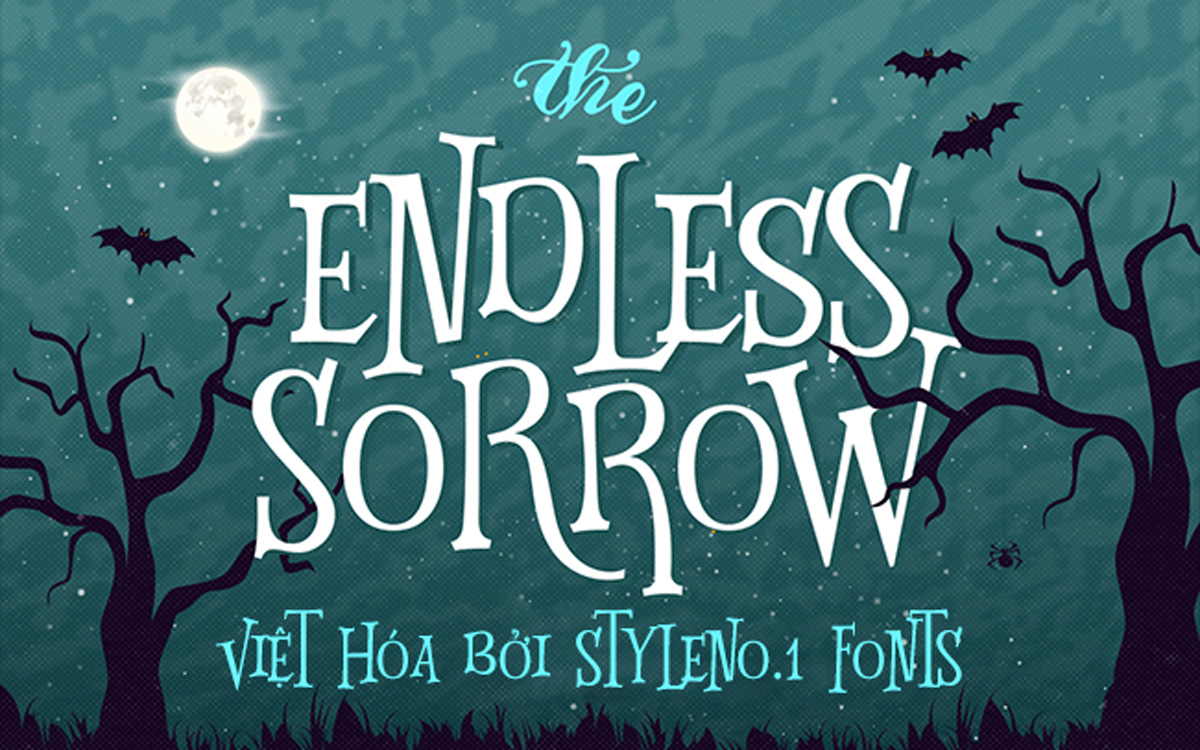
SVN-Endless Sorrow là font chữ mang phong cách hoạt hình pha trộn yếu tố kinh dị, nguy hiểm và bí ẩn, phù hợp với những thiết kế cần tạo ấn tượng mạnh ngay từ cái nhìn đầu tiên. Với đường nét độc đáo, giàu biểu cảm và không khí u tối đặc trưng, font chữ này có thể giúp tiêu đề, poster hoặc hình ảnh truyền thông trở nên nổi bật, khác biệt và dễ ghi nhớ hơn.
Không chỉ dành cho các dự án về Halloween hay phim kinh dị, SVN-Endless Sorrow còn có thể được ứng dụng trong thiết kế trò chơi, truyện tranh, sản phẩm giải trí, nội dung mạng xã hội và nhiều ấn phẩm sáng tạo khác. Nếu bạn đang tìm kiếm một kiểu chữ vừa có nét hoạt hình, vừa gợi cảm giác rùng rợn và nguy hiểm, đây là lựa chọn đáng để cân nhắc.
Font chữ hoạt hình, kinh dị nguy hiểm SVN-Endless Sorrow dành cho thiết kế sáng tạo ấn tượng
Font chữ hoạt hình, kinh dị nguy hiểm SVN-Endless Sorrow sở hữu diện mạo mạnh mẽ, khác biệt so với những kiểu chữ phổ thông thường thấy. Thiết kế của font hướng đến khả năng truyền tải cảm xúc trực tiếp thông qua hình dáng ký tự, giúp người xem nhanh chóng liên tưởng đến thế giới giả tưởng, những câu chuyện bí ẩn, không gian ma quái hoặc các tình huống đầy kịch tính.
Sự kết hợp giữa nét chữ vui nhộn theo phong cách hoạt hình và cảm giác bất an của chủ đề kinh dị tạo nên cá tính riêng cho SVN-Endless Sorrow. Nhờ đó, font có thể đóng vai trò như một yếu tố đồ họa quan trọng thay vì chỉ đơn thuần dùng để trình bày nội dung. Khi được phối hợp đúng với màu sắc, hình nền và bố cục, từng dòng chữ có thể trở thành điểm nhấn thị giác nổi bật trong toàn bộ thiết kế.
Phong cách hoạt hình kinh dị giàu cá tính
Điểm thu hút đầu tiên của SVN-Endless Sorrow nằm ở phong cách tạo hình mang tính biểu cảm cao. Các ký tự gợi cảm giác như được lấy ra từ một bộ phim hoạt hình kinh dị, một cuốn truyện tranh kỳ bí hoặc thế giới trò chơi chứa đầy thử thách. Tinh thần nguy hiểm, bất thường và có phần tinh nghịch giúp font tạo được dấu ấn riêng mà không cần sử dụng quá nhiều hiệu ứng trang trí phức tạp.
Đặc trưng này đặc biệt hữu ích khi thiết kế tiêu đề lớn, tên dự án, logo chữ, tên nhân vật hoặc những câu khẩu hiệu ngắn. Font có thể thu hút ánh nhìn nhanh chóng, đồng thời giúp người xem nhận biết chủ đề của sản phẩm ngay từ phần chữ. Để đạt hiệu quả tốt, bạn nên ưu tiên sử dụng SVN-Endless Sorrow cho các nội dung cần nhấn mạnh, thay vì dùng cho những đoạn văn dài đòi hỏi khả năng đọc liên tục.
Tạo tiêu đề nổi bật cho poster và ấn phẩm truyền thông
SVN-Endless Sorrow phù hợp để xây dựng tiêu đề có kích thước lớn trên poster phim, banner quảng cáo, bìa truyện, ảnh thumbnail, tờ rơi hoặc các ấn phẩm truyền thông theo chủ đề. Hình dáng chữ giàu cảm xúc giúp tiêu đề trở thành tâm điểm của bố cục, nhất là khi đặt trên nền tối, nền có chất liệu cũ, cảnh đêm hoặc hình ảnh mang không khí siêu nhiên.
Người thiết kế có thể khai thác font trong nhiều chủ đề khác nhau, chẳng hạn như:
- Poster Halloween, lễ hội hóa trang và chương trình giải trí theo chủ đề kinh dị.
- Bìa truyện tranh, tiểu thuyết giả tưởng, truyện ma hoặc nội dung trinh thám bí ẩn.
- Banner giới thiệu trò chơi, sự kiện nhập vai và các chiến dịch truyền thông sáng tạo.
- Thumbnail video kể chuyện, khám phá địa điểm kỳ bí hoặc phân tích phim kinh dị.
- Logo chữ cho thương hiệu giải trí, cửa hàng phụ kiện, sản phẩm nghệ thuật hoặc dự án cá nhân.
Khi ứng dụng font vào poster, bạn có thể tăng độ tương phản bằng cách sử dụng những màu sắc như đỏ sẫm, cam cháy, vàng cũ, trắng ngà hoặc xanh độc trên nền đen. Tuy nhiên, nên tiết chế số lượng hiệu ứng để giữ được hình dáng nguyên bản và khả năng nhận diện của từng ký tự.
Linh hoạt trong thiết kế nội dung số và mạng xã hội
Bên cạnh các ấn phẩm in, font chữ hoạt hình kinh dị SVN-Endless Sorrow còn có thể hỗ trợ sáng tạo nội dung trên môi trường số. Font phù hợp với ảnh bài đăng, ảnh bìa, tiêu đề video, giao diện trò chơi, nội dung quảng bá sự kiện hoặc hình ảnh giới thiệu sản phẩm theo phong cách cá tính. Một cụm từ ngắn được trình bày bằng kiểu chữ này có thể tăng sức hút cho thiết kế khi người dùng lướt nhanh trên mạng xã hội.
Để font phát huy hiệu quả trên màn hình, người dùng nên lựa chọn cỡ chữ đủ lớn, tạo khoảng cách hợp lý giữa các ký tự và hạn chế đặt chữ trên nền quá nhiều chi tiết. Trong trường hợp cần trình bày thêm thông tin như thời gian, địa điểm, giá bán hoặc mô tả chương trình, bạn có thể kết hợp SVN-Endless Sorrow với một font sans serif đơn giản, dễ đọc. Cách phối hợp này vừa duy trì được không khí kinh dị ở phần tiêu đề, vừa bảo đảm nội dung phụ rõ ràng và chuyên nghiệp.
Hỗ trợ xây dựng không khí bí ẩn, nguy hiểm cho thiết kế
Kiểu chữ là một phần quan trọng trong việc định hình cảm xúc của tác phẩm. Với SVN-Endless Sorrow, người thiết kế có thể nhanh chóng tạo ra bầu không khí căng thẳng, bí ẩn hoặc ma quái mà không phải phụ thuộc hoàn toàn vào hình minh họa. Chỉ riêng phần tiêu đề cũng có khả năng gợi mở về một câu chuyện chưa được giải đáp, một nhân vật kỳ lạ hoặc mối nguy hiểm đang ẩn giấu.